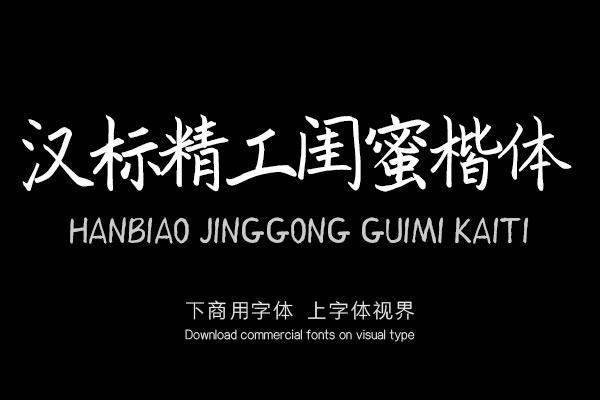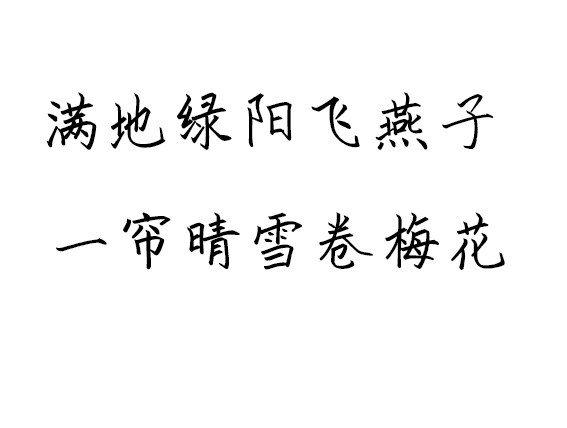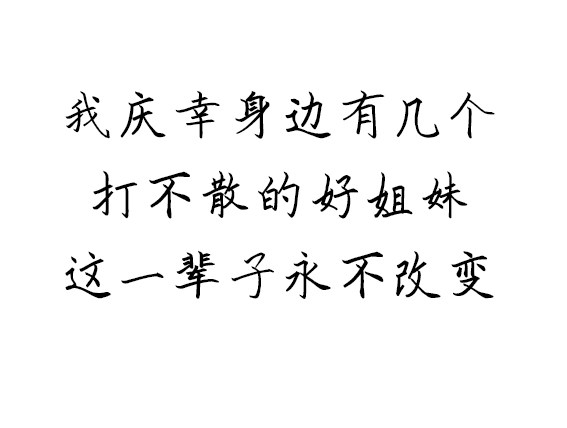
汉标精工闺蜜楷体|原创手写字体
原创手写字体,你受辱,我替你讨公道。你不开心,我逗你笑。你开心,我陪你二。谁欺负你,我批判谁。你心里不痛快了,我替你当泼妇撒泼,我是你的闺蜜,没毛病。
汉标精工闺蜜楷体
该字体脱胎于传统的书法字体,笔画和结构取自传统书法,保留传统书法韵味,同时采用更大的中宫,所以它淡雅、隽秀、易阅读,让使用者有清新自然、富有韵律的阅读体验。适用于文艺类的书刊、品牌广告和产品包装设计,以及社交网络的个性化用字。
汉标精工闺蜜楷体